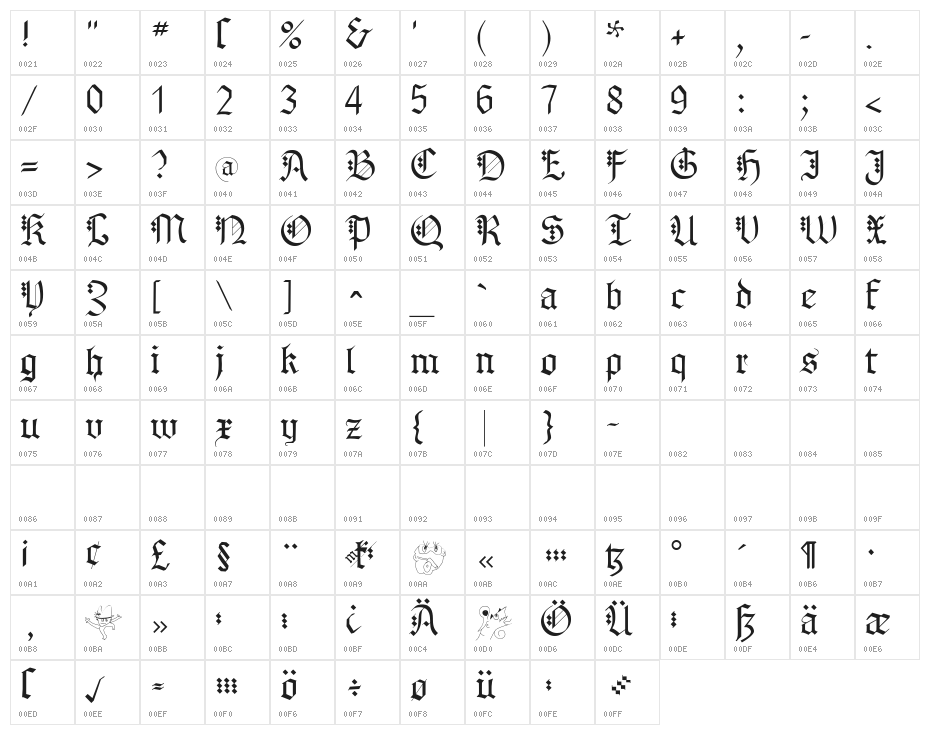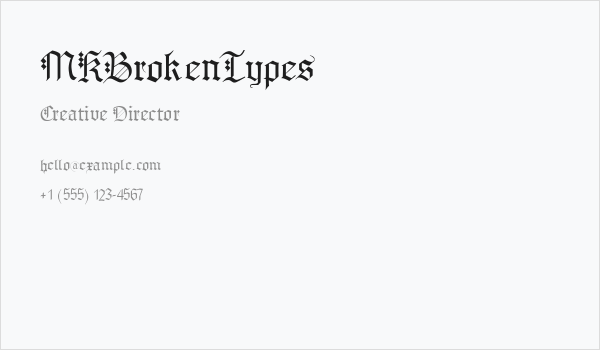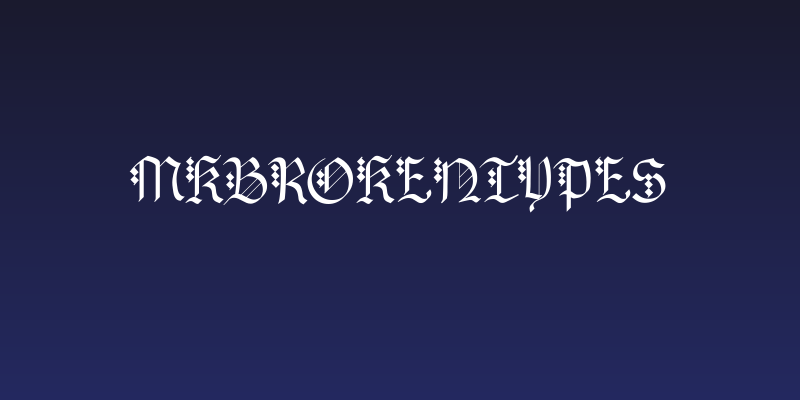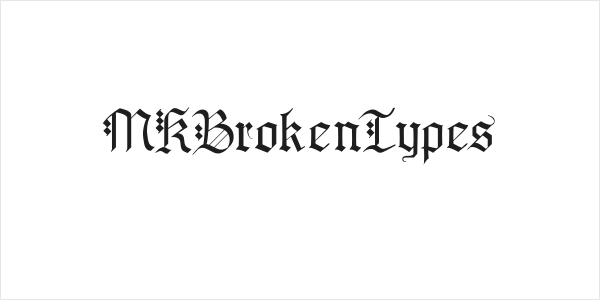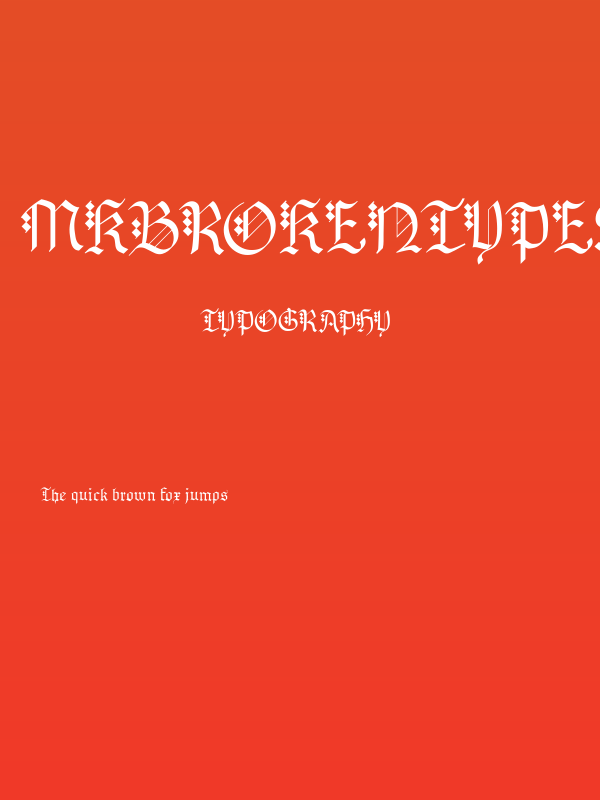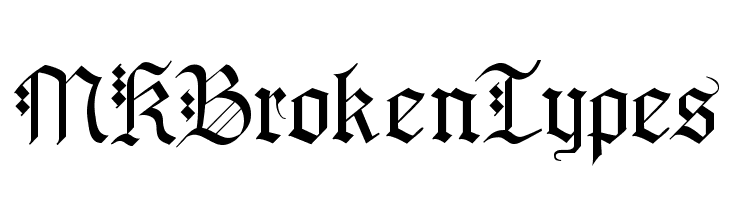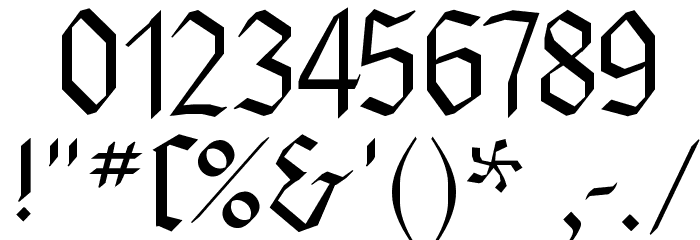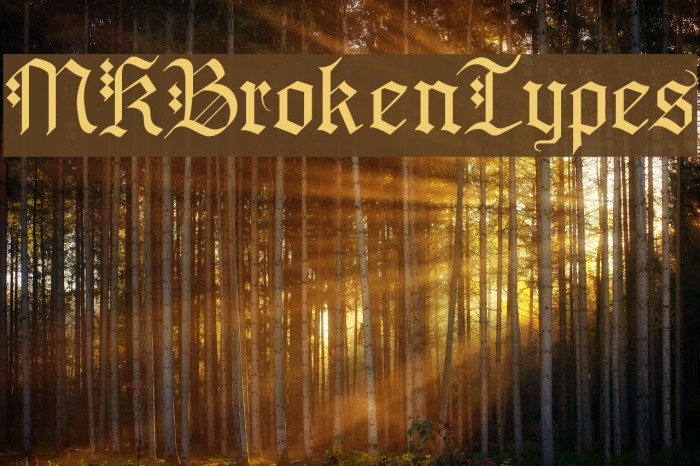
MKBrokenTypes Font
✎ Gothic
| Категория | Gothic |
| Общий стиль | Vintage |
| Область применения | Headlines, Logos, Decorative text |
| Рекомендуемые проекты | Ideal for projects requiring a historical or traditional feel, such as event invitations, certificates, or branding for vintage-themed products. |